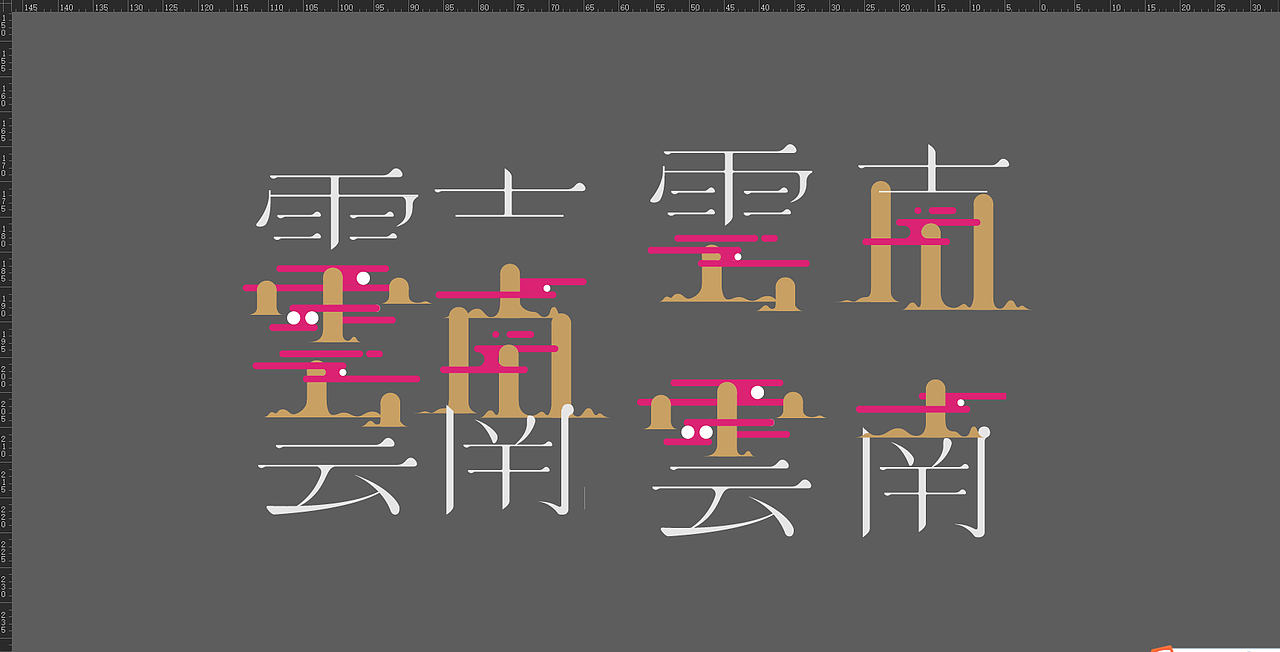
毕业采风去了云南,回来学校学校要求做一本册子
于是乎就出了,这本册子,连封面封底44P
后续由于学校要对我们做的册子开展览,又做了一张海报,由于比较懒,直接把海报做成书的封面了。
之前只传了一部分,现在把余下的和制作过程中的尝试都放上来
封面
封底
然后这个是我使用的网格系统
这个是做海报的时候专门做的一个字体,个人最喜欢的就是这字体
这是期间的各种组合方式尝试,打算把文字和图形文字结合到一起,但最后感觉效果都一般,最后还是图形文字和文字分开使用
最终打印出来的是这个版本
我个人比较喜欢这个骚情的荧光桃红